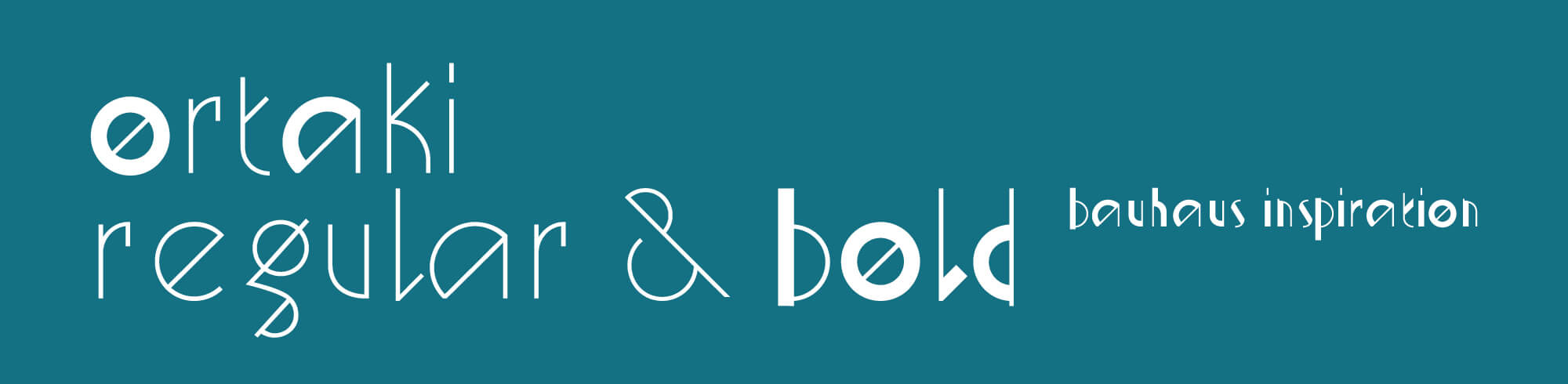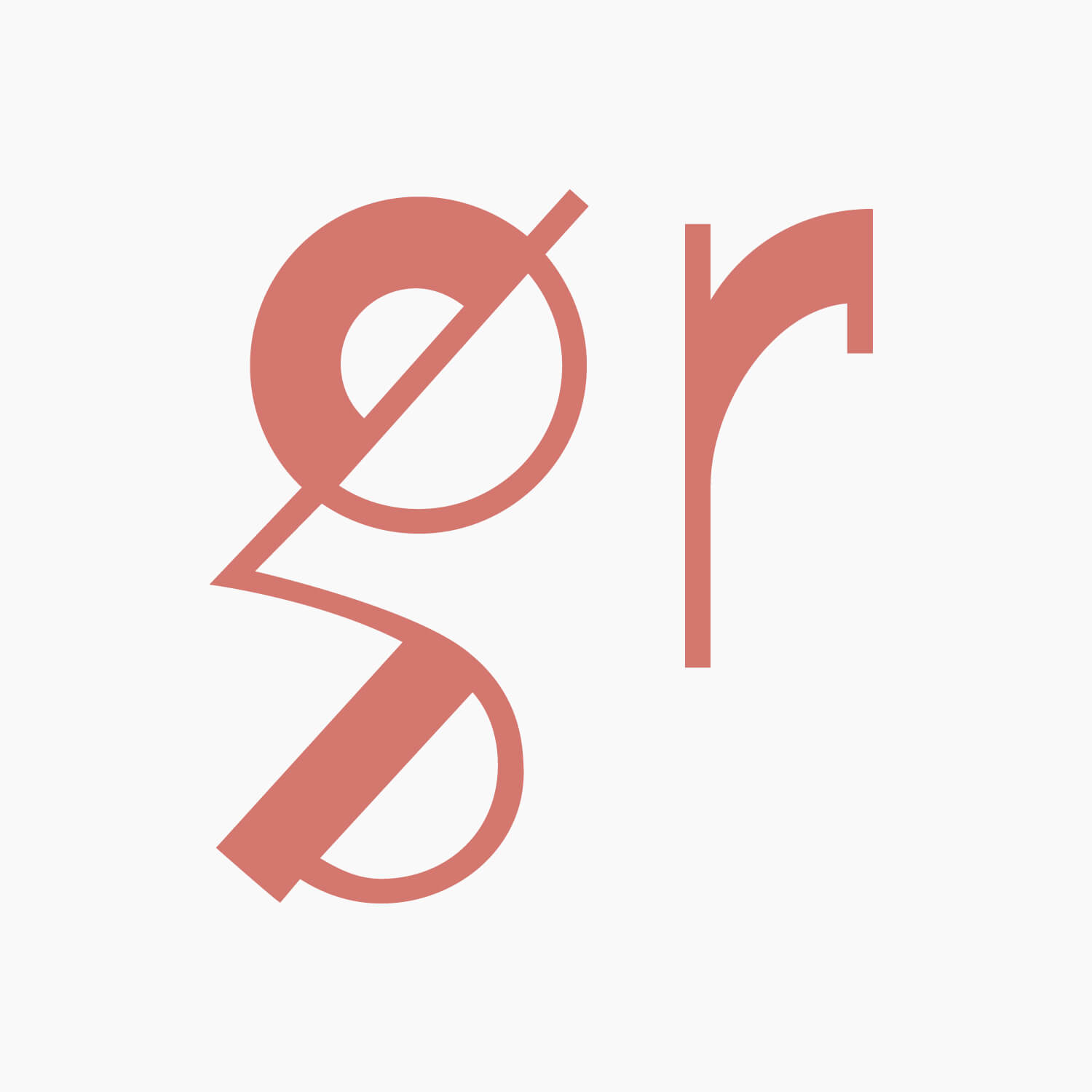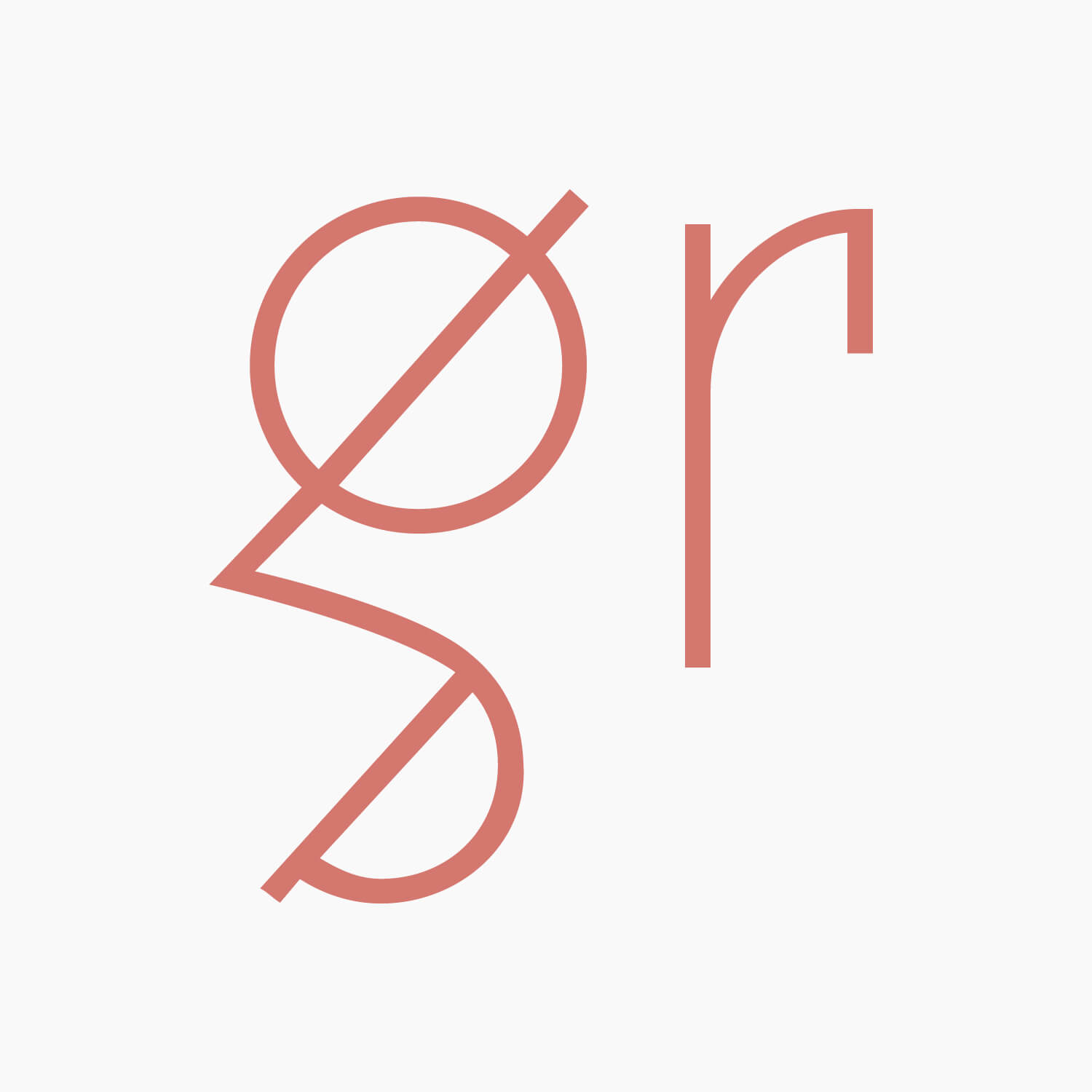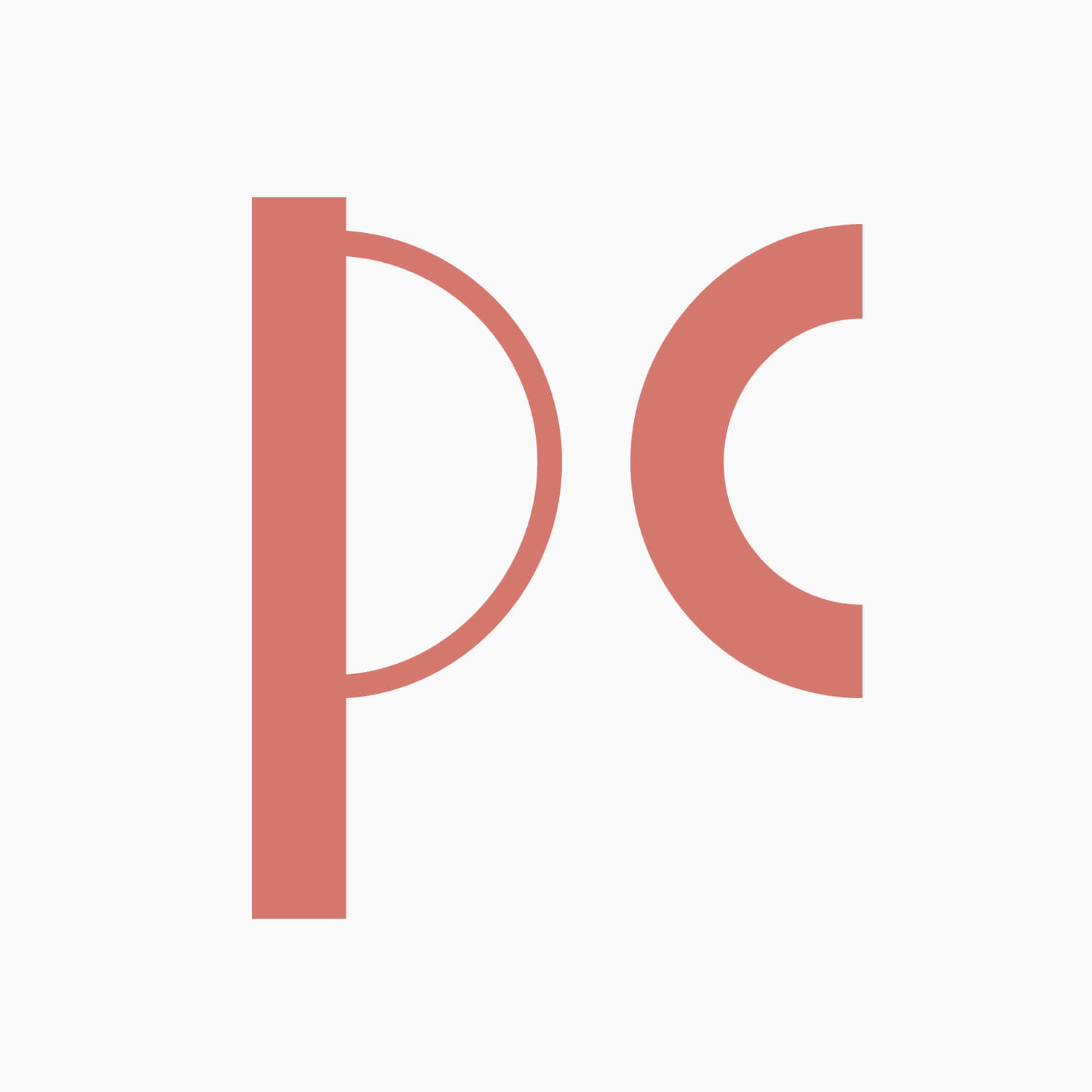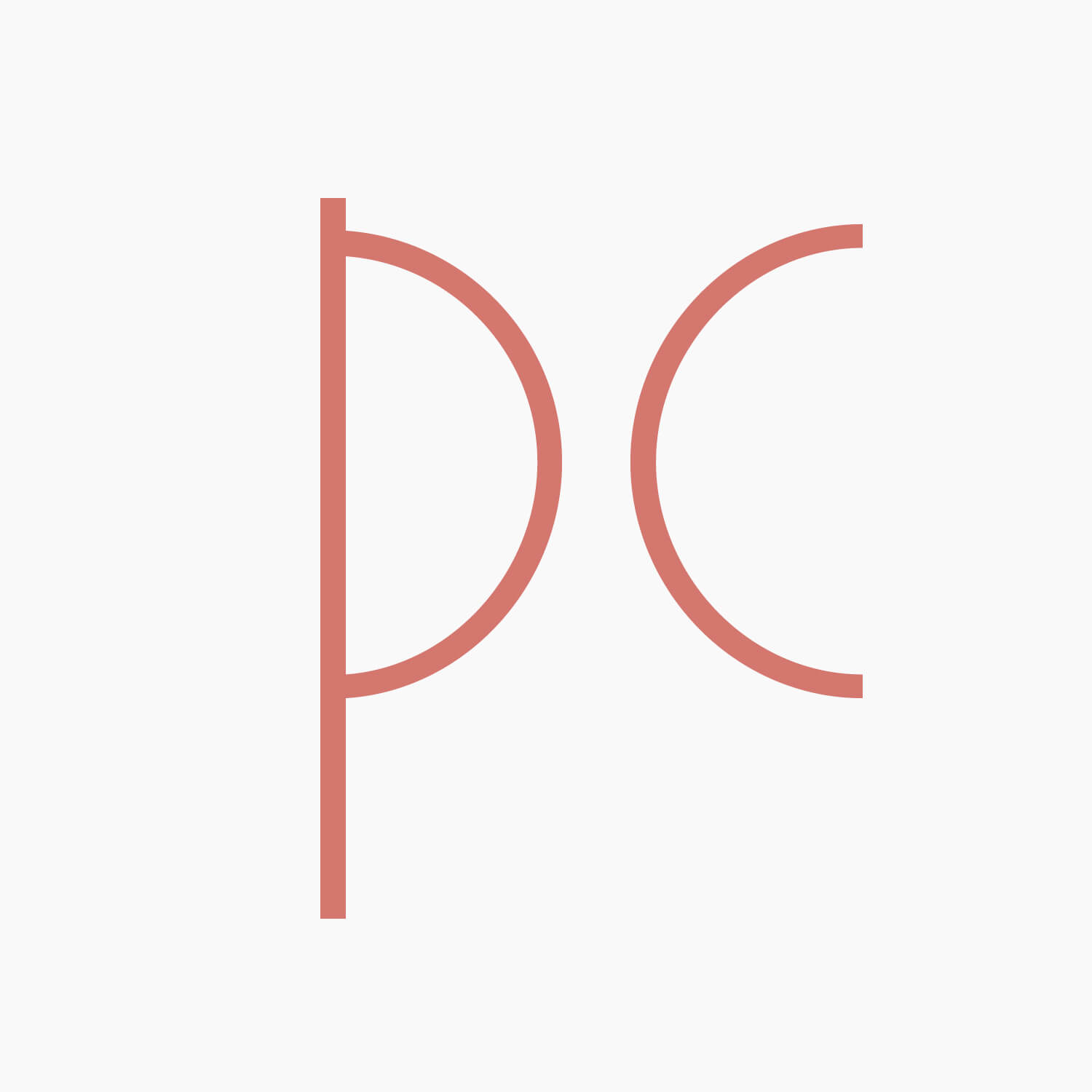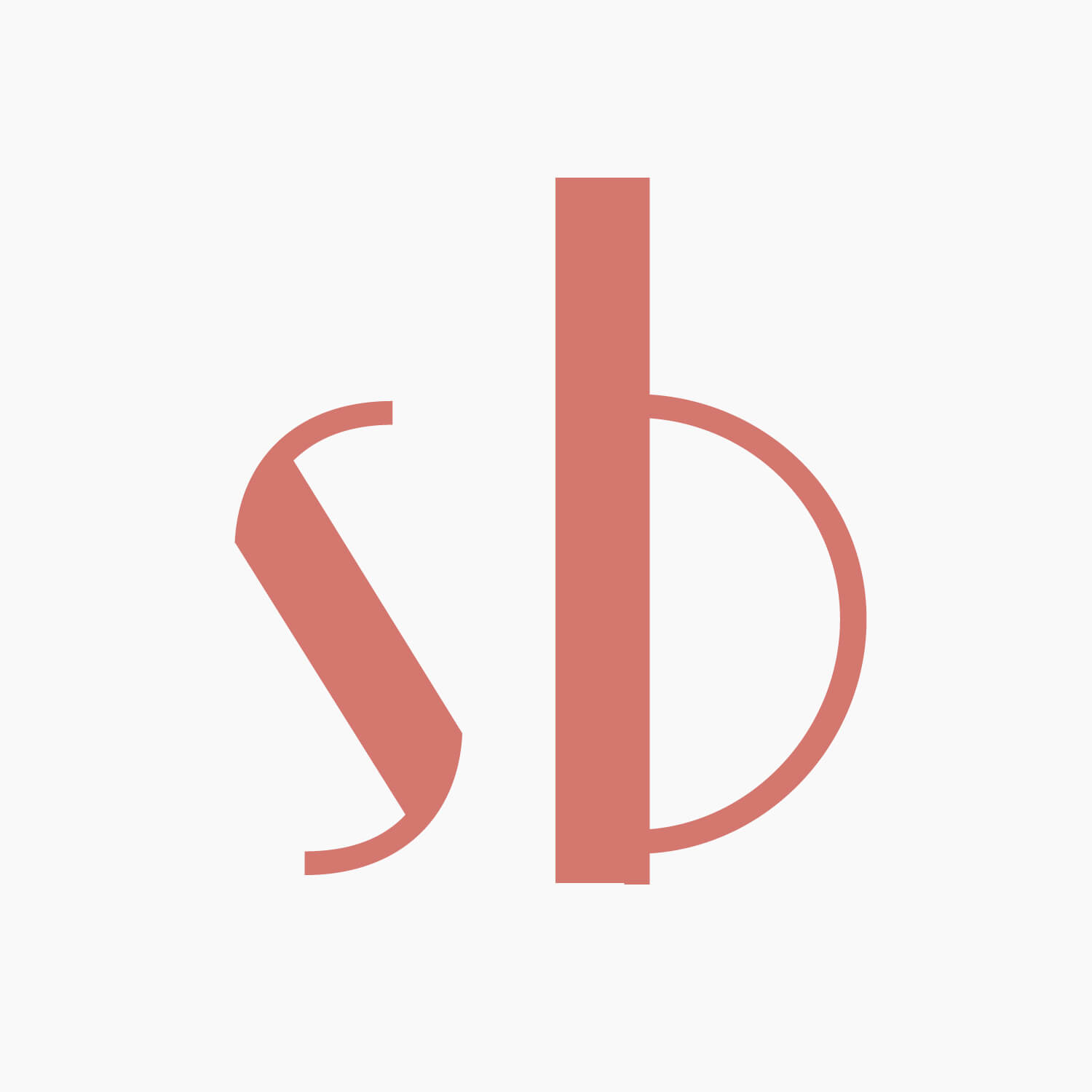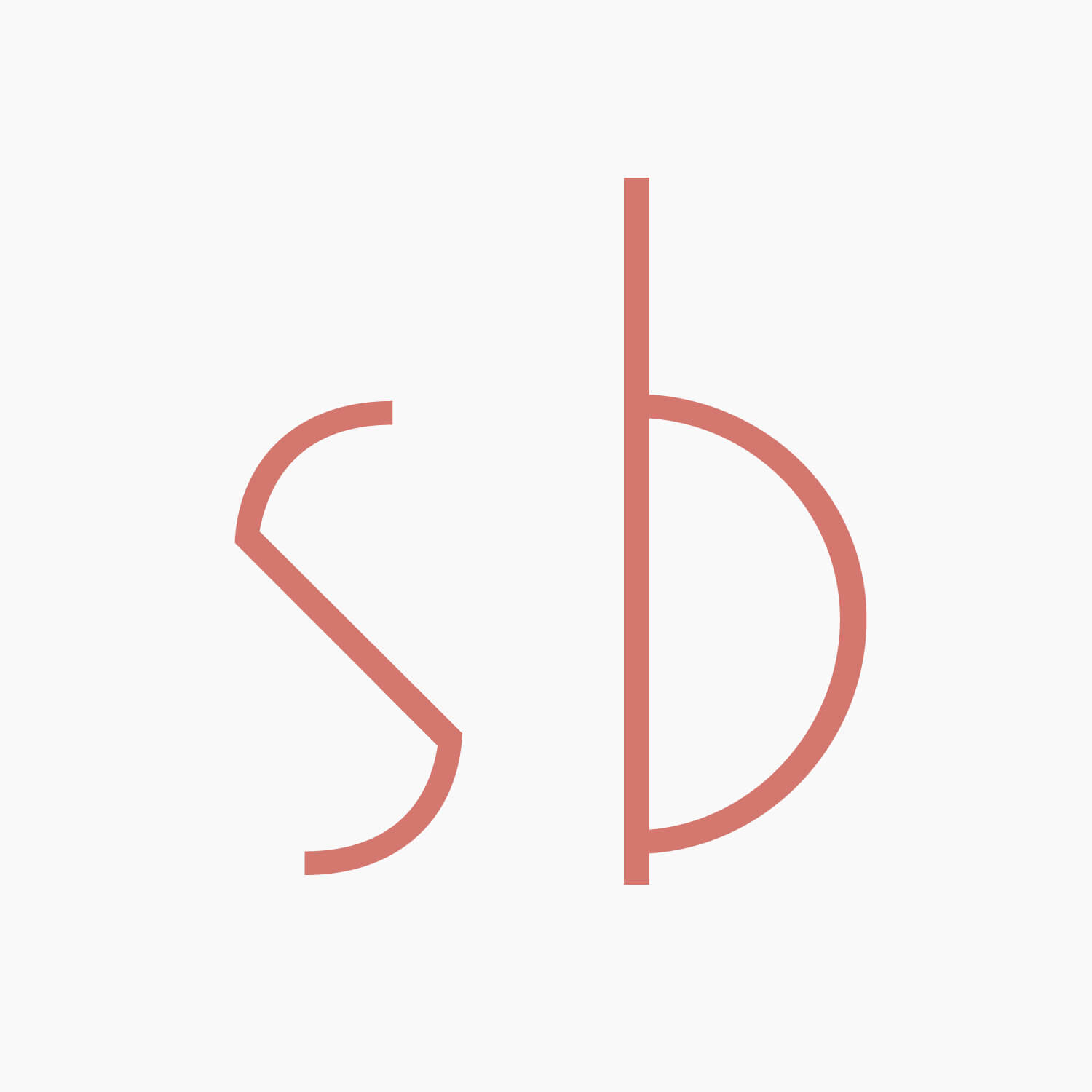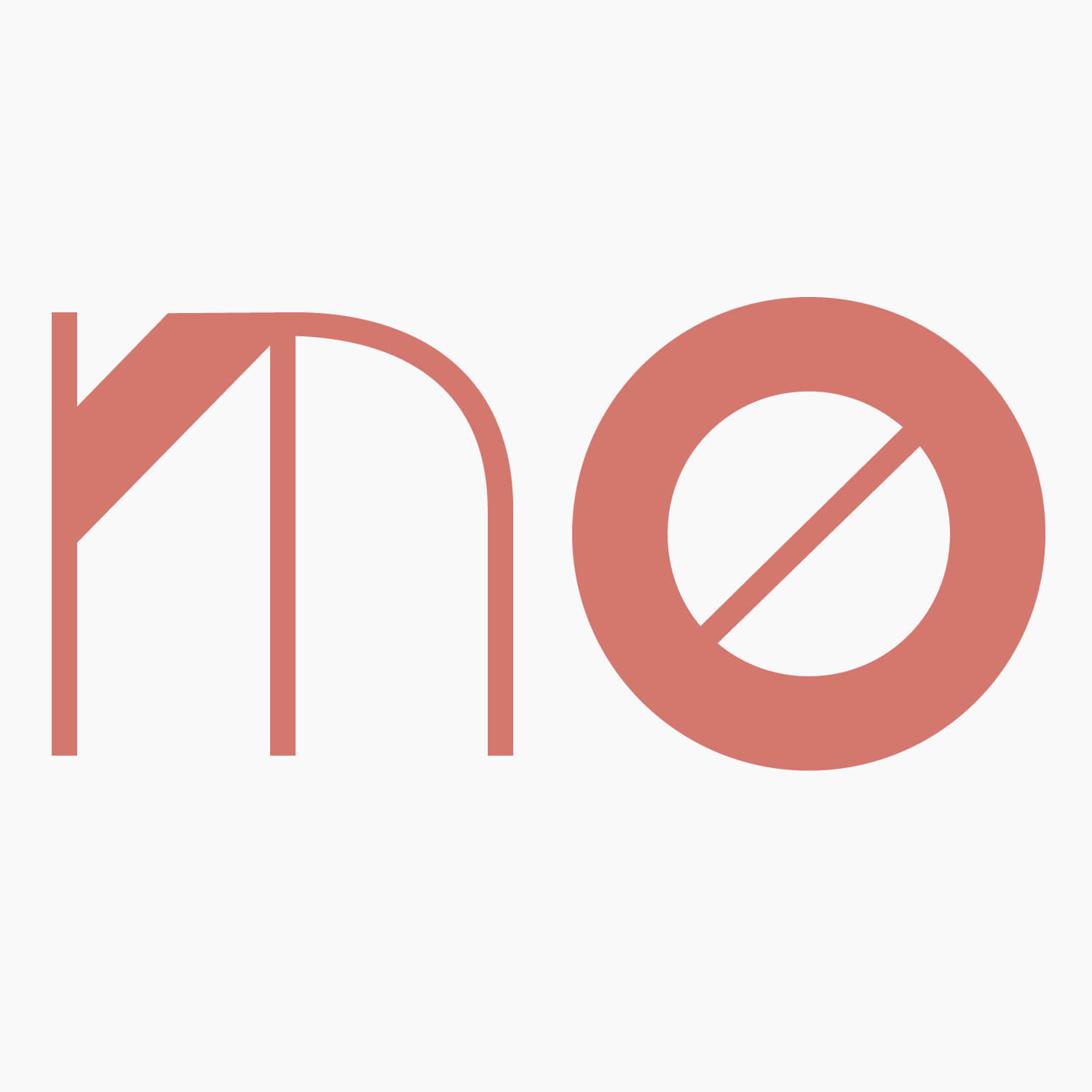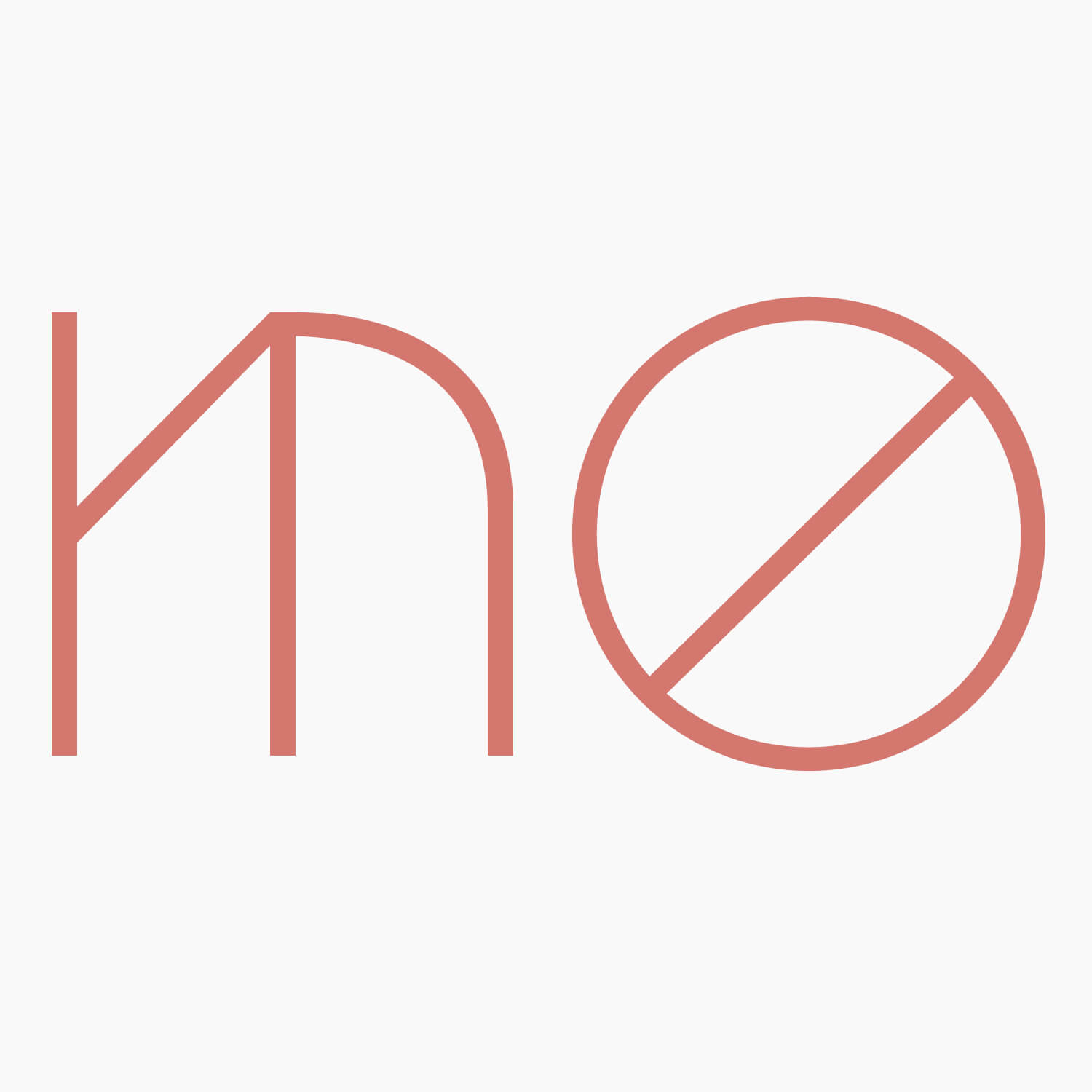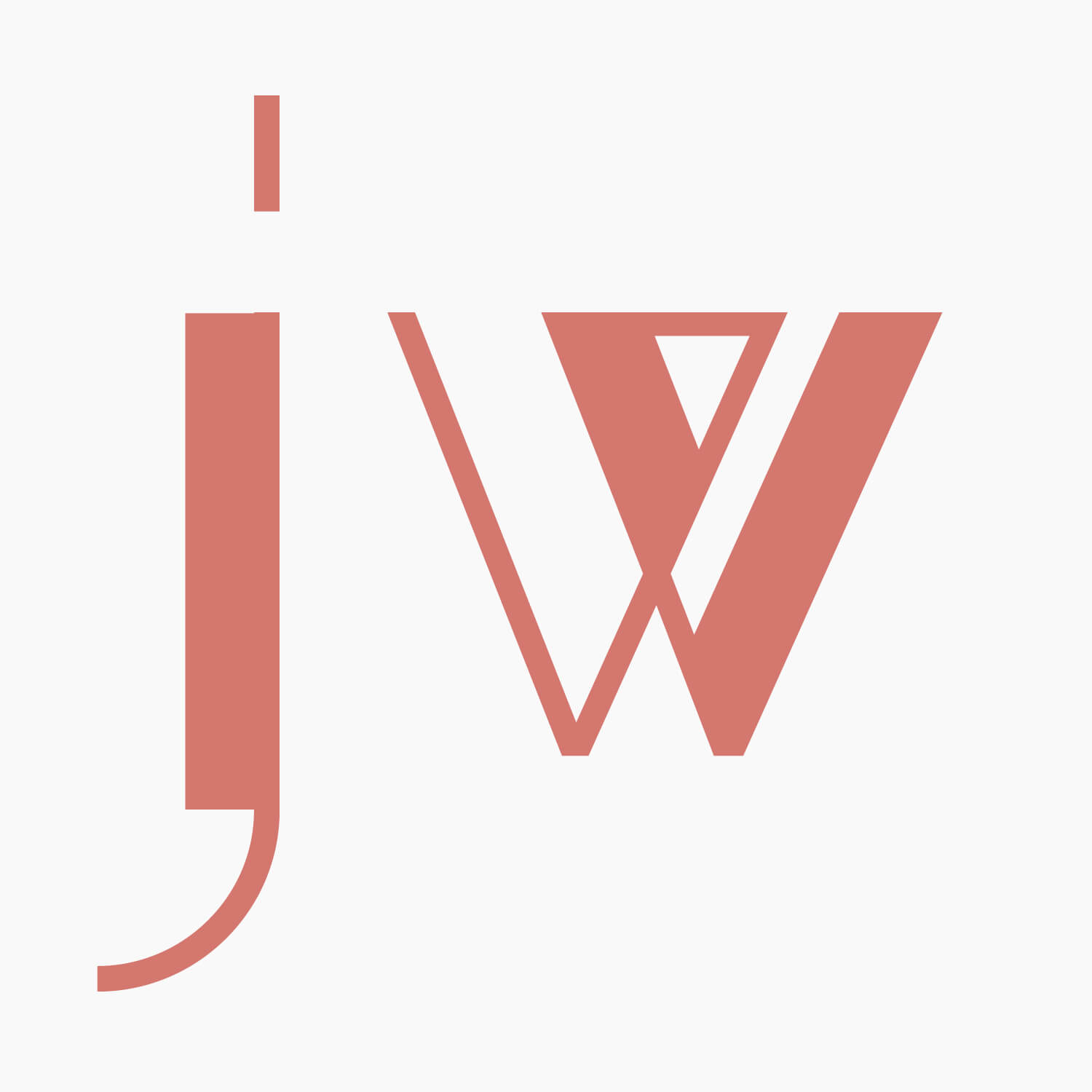
L’ortaki est une typographie géométrique expérimentale inspirée du Bauhaus et dessinée principalement pour les titres. Elle existe en deux graisses, regular et bold.